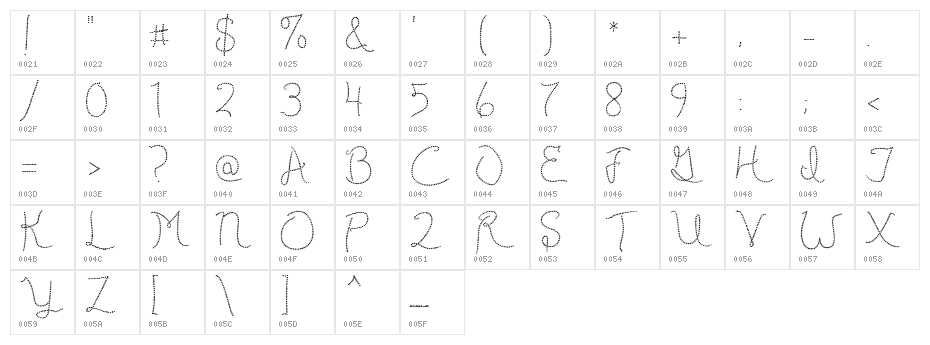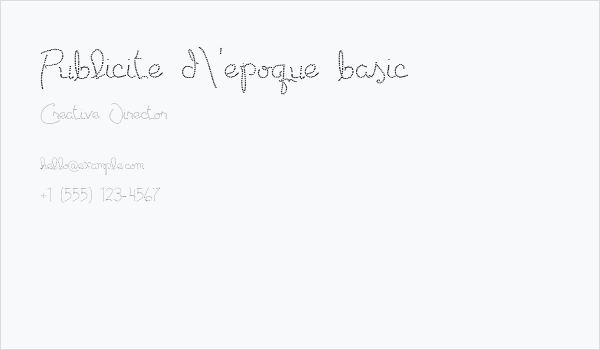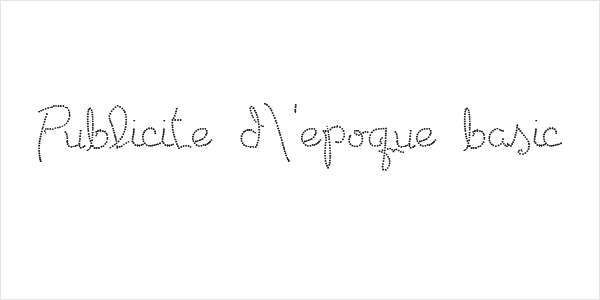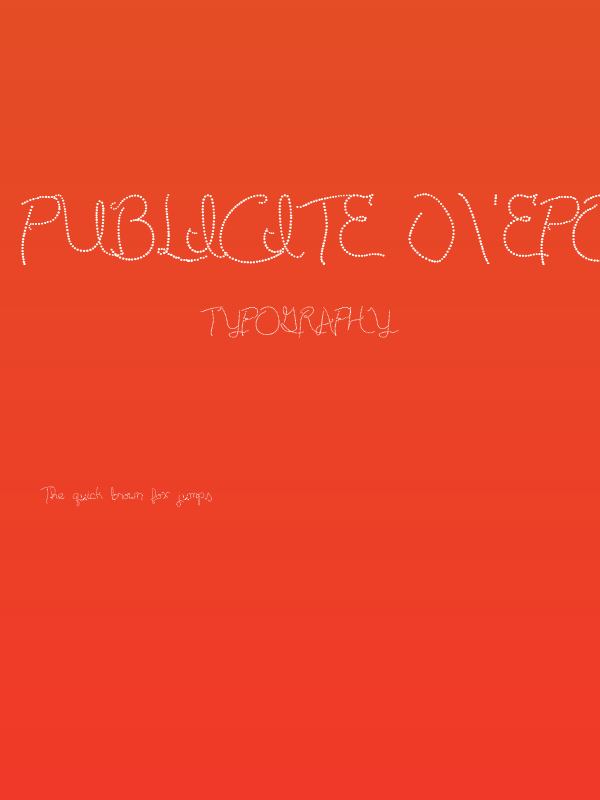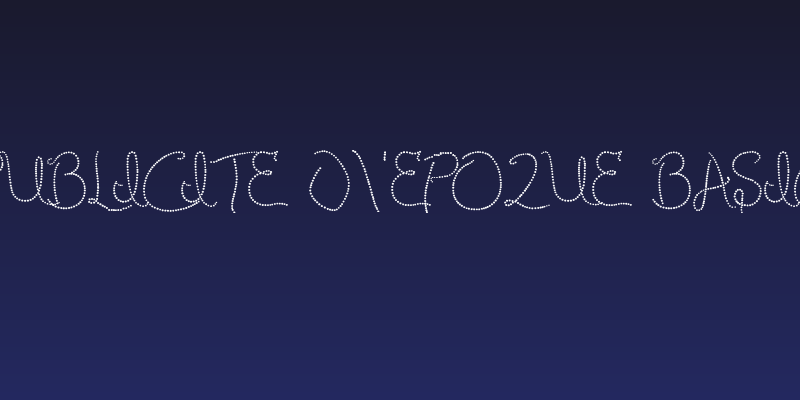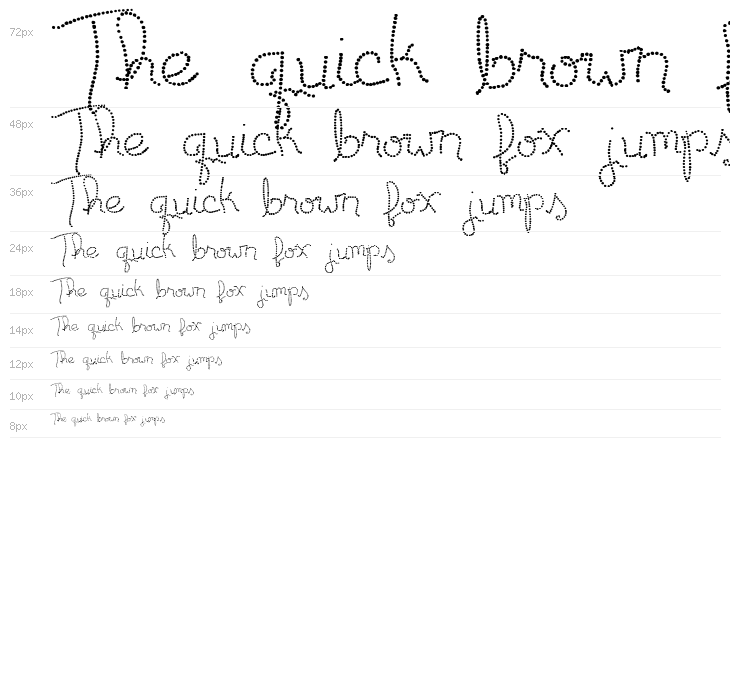
Publicite d'epoque basic Font
| Caso d'uso | Headlines, Logos, Decorative text |
| Progetti proposti | Ideal for vintage-themed posters, creative invitations, playful branding, and decorative signage. |